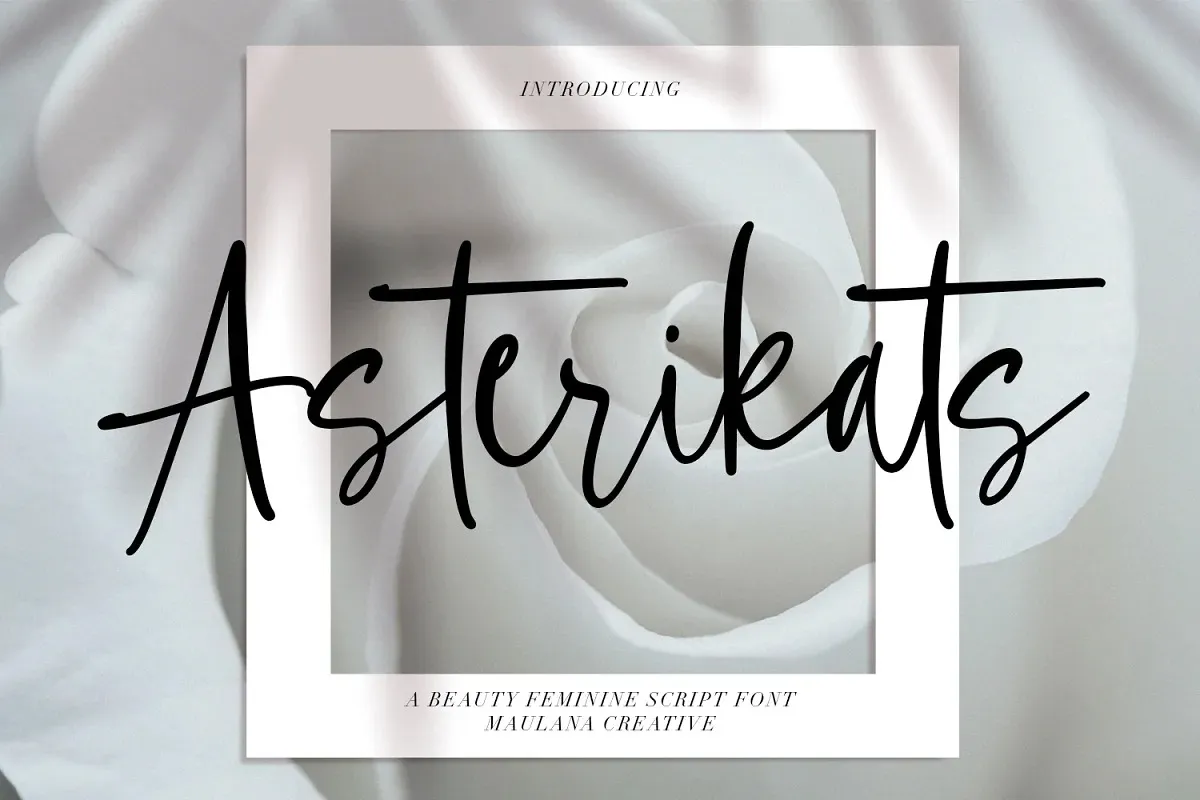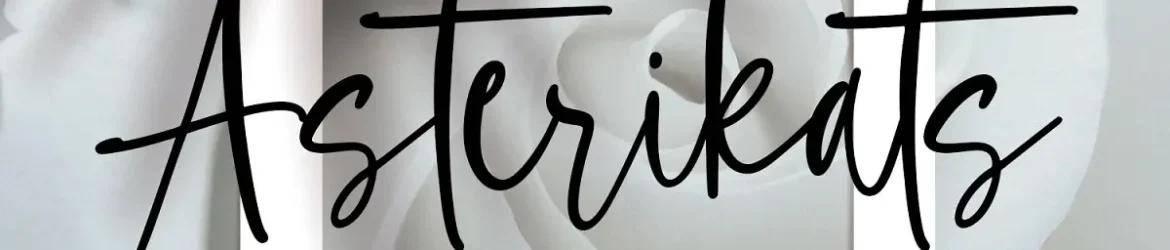
Asterikats Font – Download Grátis
Asterikats é uma fonte script moderna que revela a beleza e sofisticação. Ela foi criada por Maulana Creative, um designer de fontes renomado. A Asterikats Beauty Feminine possui uma escrita natural, proporcionando uma sensação de leveza e elegância perfeita para projetos variados como Headline, Invites, Logotipos, Lançamentos de Voo e outras áreas de design. Suave mas poderosa, esta fonte é ideal para aquelas necessidades que precisam de um tipo específico, seja para sua camiseta ou seu banner publicitário. Aprovado por especialistas em design, ela se adapta perfeitamente a um amplo espectro de aplicações, tornando-a uma escolha confiável para designers profissionais e amadores que desejam dar aos seus projetos um toque único e sofisticado.